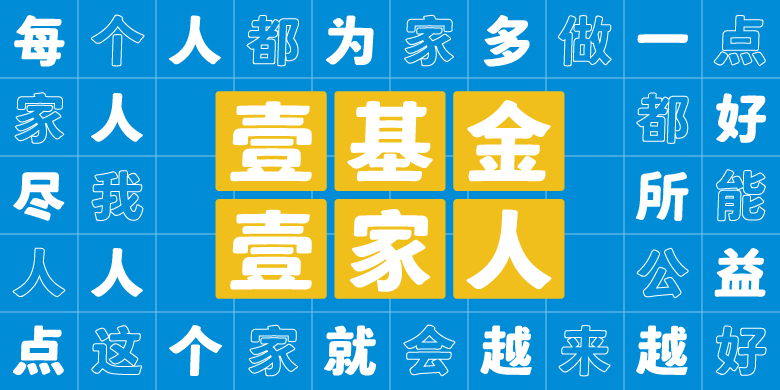
字體名稱: 方正壹基金壹家
方正壹基金壹家人體
方正壹基金壹家人體是由壹基金與方正字庫聯(lián)合開發(fā)的國內第一款公益品牌聯(lián)名字體,以文字這一獨特介質傳播“壹家人”理念。這款字體不僅設計優(yōu)美,適用于廣告、包裝等各類場景,而且字體售賣部分收入將用于壹基金的公益項目,幫助弱勢群體改善困境。 方正壹基金壹家人體由方正字庫設計總監(jiān)仇寅帶領團隊設計,現(xiàn)代黑體融入了圓體與手寫體的特點,新穎、獨特的導圓處理和“喇叭口”設計、豎筆畫使用了前傾2°的處理,在原本平穩(wěn)的黑體上增添了書寫意味,圓潤飽滿,凸顯親和友好的字體形象。